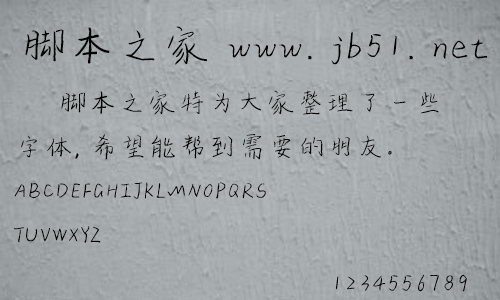
可可花陌體一款不錯(cuò)的藝術(shù)字體,這款字體筆觸較為纖細(xì),書(shū)寫隨性灑脫,具有很好的視覺(jué)感,適合應(yīng)用于藝術(shù)設(shè)計(jì)、平面宣傳設(shè)計(jì)、網(wǎng)頁(yè)設(shè)計(jì),書(shū)法字帖等領(lǐng)域。需要的朋友快來(lái)本站下載使用吧!